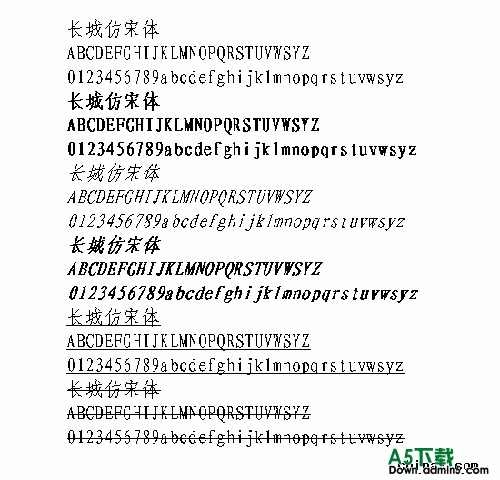
長(zhǎng)城仿宋體
長(zhǎng)城仿宋體簡(jiǎn)介
長(zhǎng)城仿宋體是一種較長(zhǎng)的仿宋字體,長(zhǎng)城仿宋體是主要用于工程制圖中的標(biāo)準(zhǔn)用字體,是專(zhuān)業(yè)性極強(qiáng)的中文漢字字體,易于書(shū)寫(xiě),規(guī)范美觀,廣泛應(yīng)用于工程設(shè)計(jì)行業(yè)。